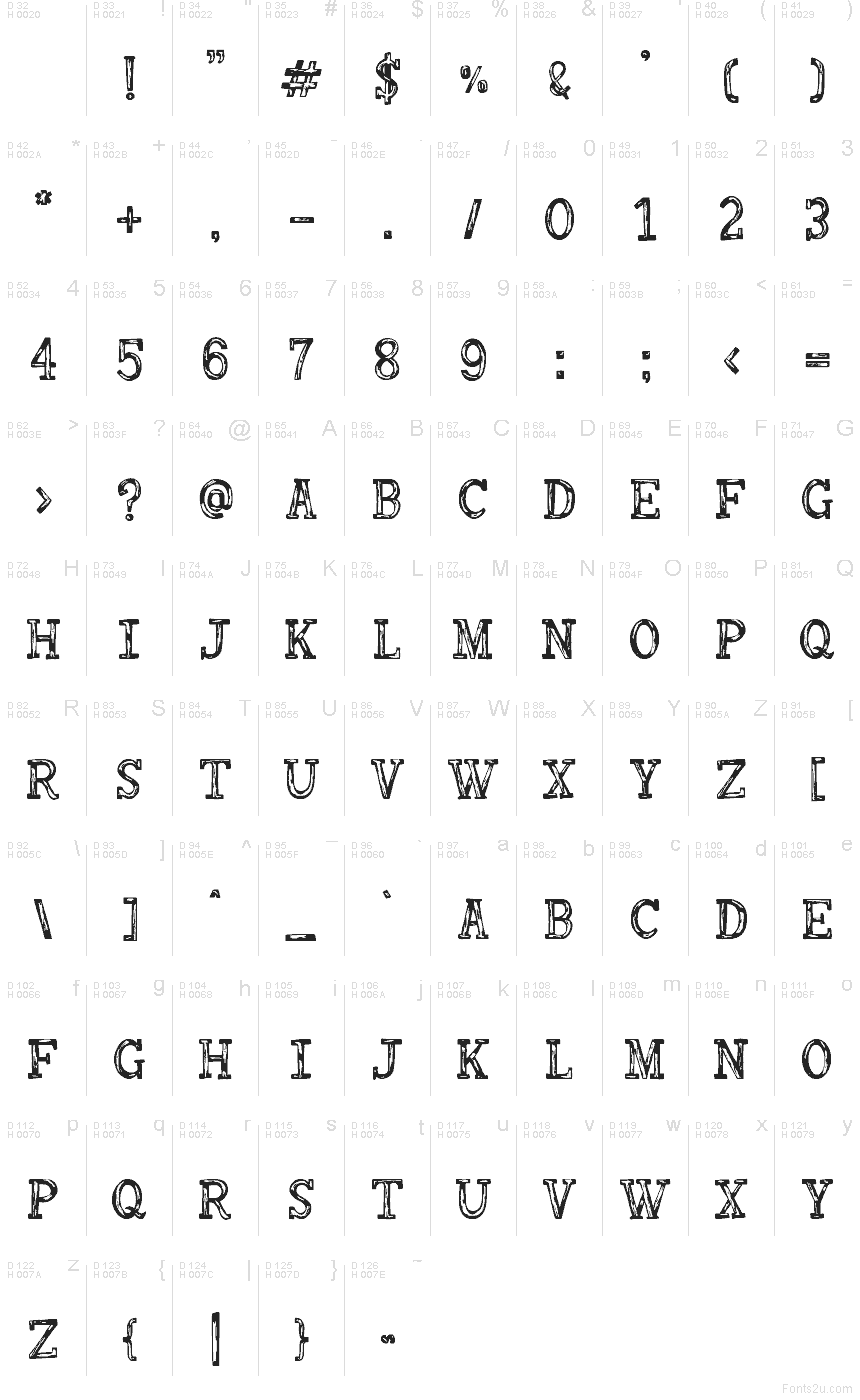
Cultura Estropeada, créée par Woodcutter Manero, est une police display vintage serif avec un effet usé qui rappelle les anciennes lettres en bois de typographie traditionnelle. Les caractères semblent abîmés, ébréchés et légèrement irréguliers ; avec leurs empattements massifs et leurs bords rugueux, ils confèrent à l'ensemble un rendu typique d'une vieille impression, loin de la finition numérique lisse.
Elle est idéale pour les titres d'affiches, les couvertures de livres, le packaging ou l'identité visuelle de cafés et bars où cette esthétique imprimée apporte tout son caractère. En tant que police gratuite, elle est particulièrement efficace pour les textes courts, les monogrammes et les grands titres, car sa texture marquée et ses formes rétro imposantes captent immédiatement l'attention.
Ruined Culture.